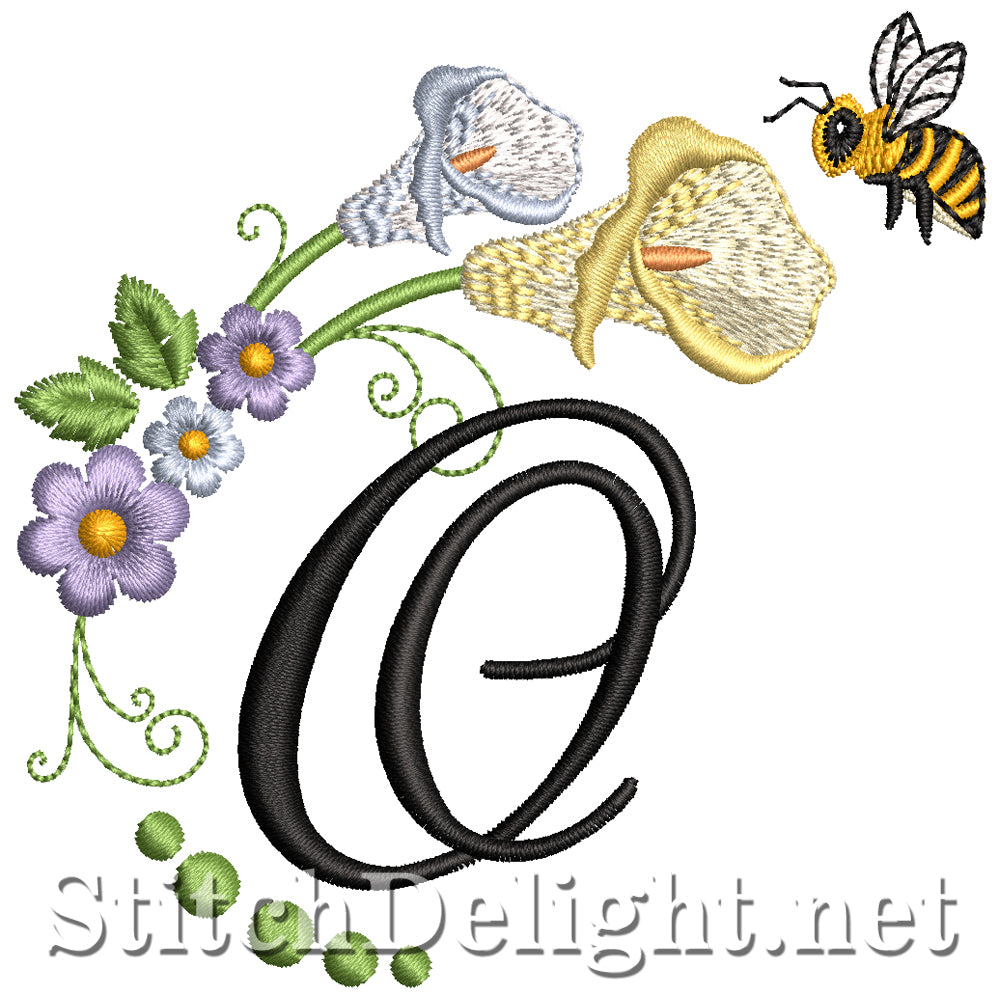
SDS2601 Spring Blossom Police O
Une autre belle police créée par Stitch Delight, il s'agit d'une seule lettre de la police conçue pour le cerceau 4x4. Cette police est parfaite pour les maisons d'hôtes souhaitant broder leur nom sur le linge, les taies d'oreiller !